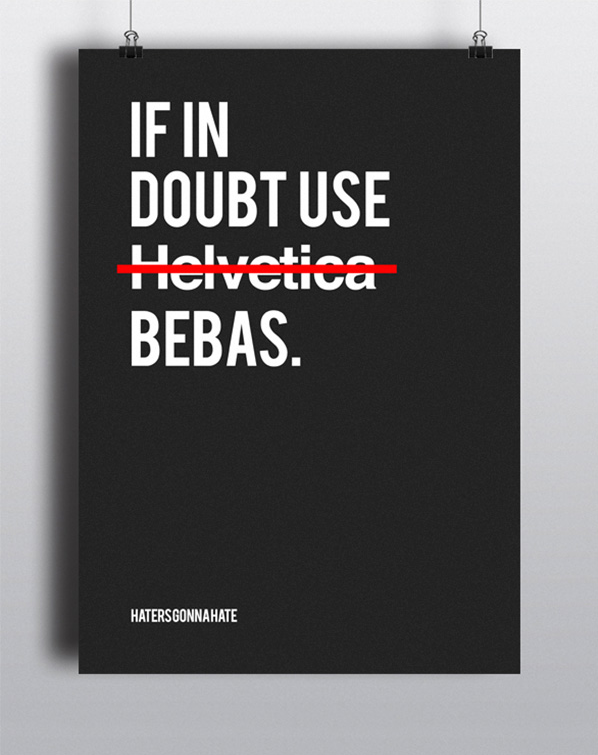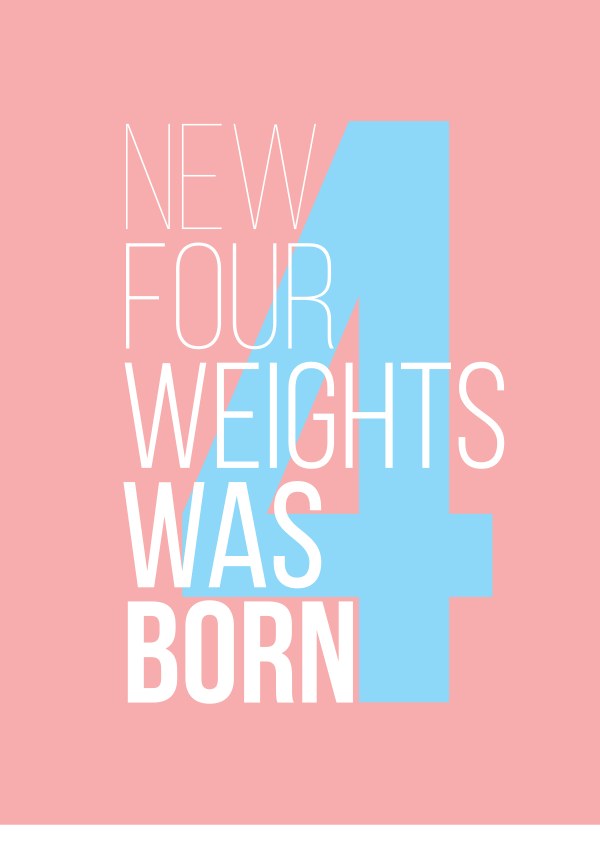
Un repaso en el diseño del 2014 nos trae infinidad de logos hechos en Neutra, folletos en Helvética Neue y Facebook y Pinterest plagado de posteos “inspiradores” en Sue Ellen Francisco (¿de dónde habrá salido esta reencarnación infernal de la Comic Sans?). Gente, esto tiene que parar.
Como buen diseñador suele estar a la caza y recomienda constantemente entre sus seguidores de Twitter las diferentes tipografías gratuitas que va encontrando por la web. Así que le pedimos que nos armara una lista de 10 tipografías gratuitas, las únicas que vamos a necesitar usar en este 2015 para hacer del diseño algo brillante. Acá están, estas son:
BEBAS
WISDOM SCRIPT
CHOPLIN
SANT JOAN
HANS KENDRICK
BIZON
FORUM
FLAGSHIP
AHAMONO
KLINIC